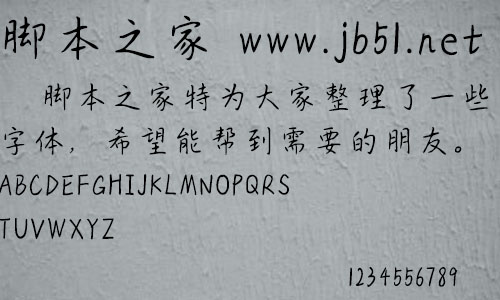
漢儀青春里的路人一款不錯(cuò)的藝術(shù)字體,由漢儀字庫(kù)出品,字體筆觸適中,書(shū)寫(xiě)流暢,具有很好的視覺(jué)感,適合應(yīng)用于藝術(shù)設(shè)計(jì)、平面宣傳設(shè)計(jì)、網(wǎng)頁(yè)設(shè)計(jì),書(shū)法字帖等領(lǐng)域,需要的朋友可以前來(lái)本站下載。